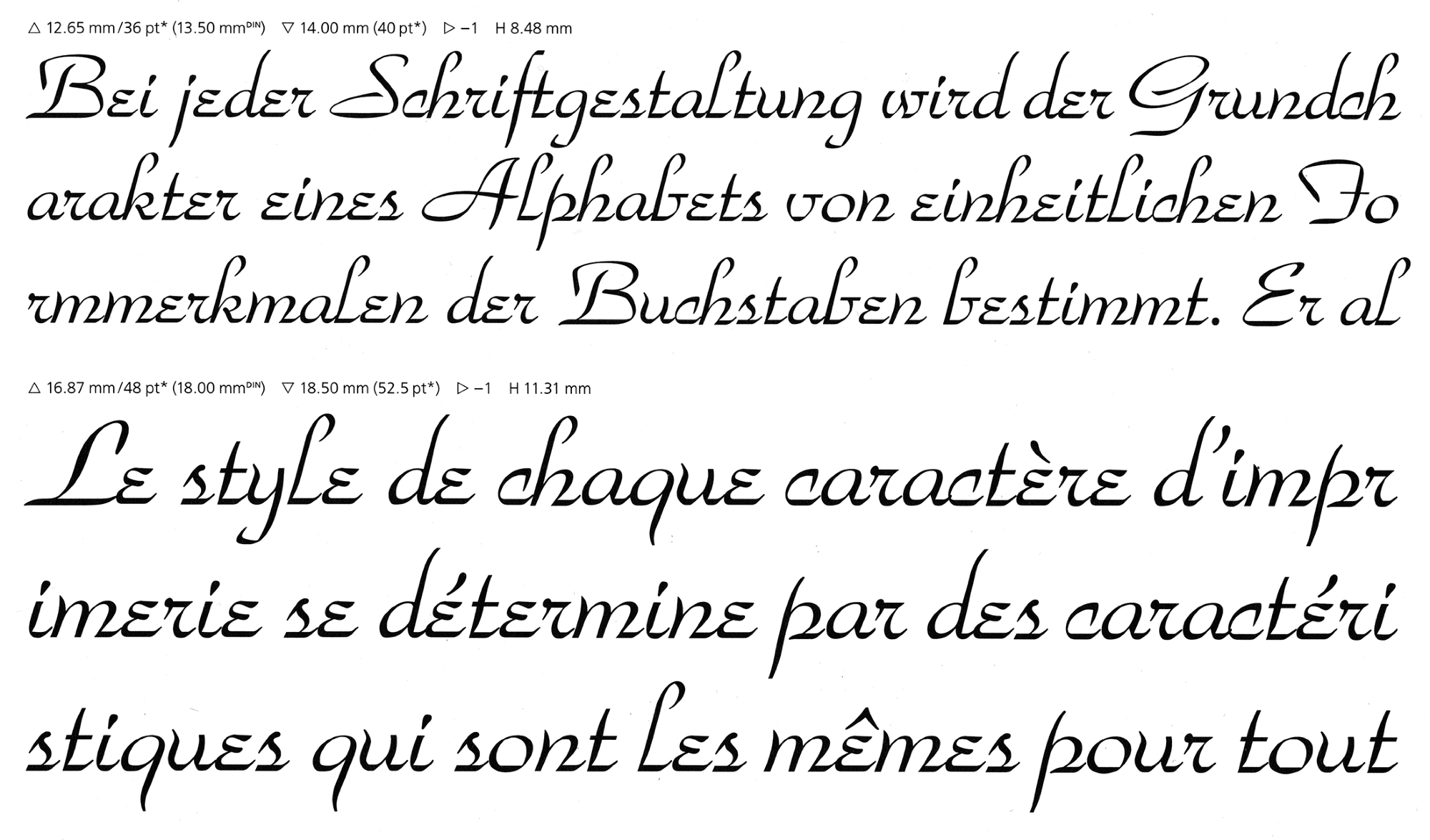
Font-Wiki: Park Avenue
Die Schreibschrift Park Avenue von Robert E. Smith erschien 1933 bei American Type Founders als Bleisatzschrift. Die Schrift war wie Smiths »Brush Script« im 20. Jahrhundert in den USA eine vielfach eingesetzte Schaugrößenschrift und wurde in der Folge auch für den Foto- und Digitalsatz adaptiert.
Digitale Versionen gibt es heute zum Beispiel von Linotype, URW und Bitstream.